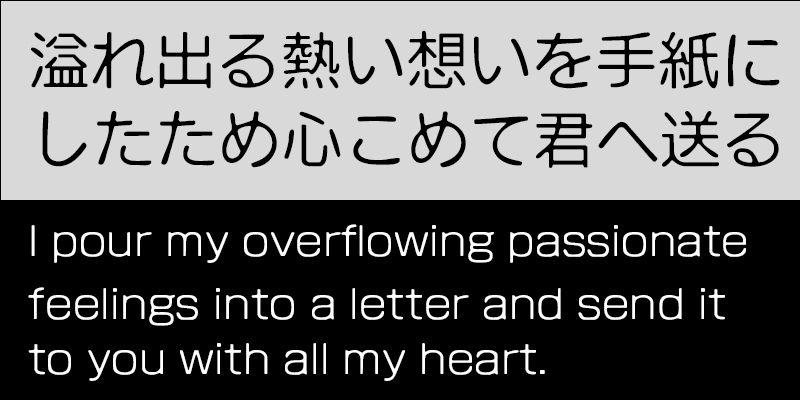
Auf die Formen der Shizuka-Gothic-Striche wird ein Verlaufseffekt angewendet, wodurch sich mit dieser Schrift Emotionen wirkungsvoll ausdrücken lassen.
TNOF Design entwickelte die Schriftfamilien Shizuka Mincho und Shizuka Gothic mit Schwerpunkt auf Lesbarkeit und Übersichtlichkeit. Shizuka Mincho ist für Fließtexte gedacht, und Shizuka Gothic mit sechs Strichstärken kann für eine Vielzahl von Anwendungen vom Fließtext bis hin zu Überschriften verwendet werden.